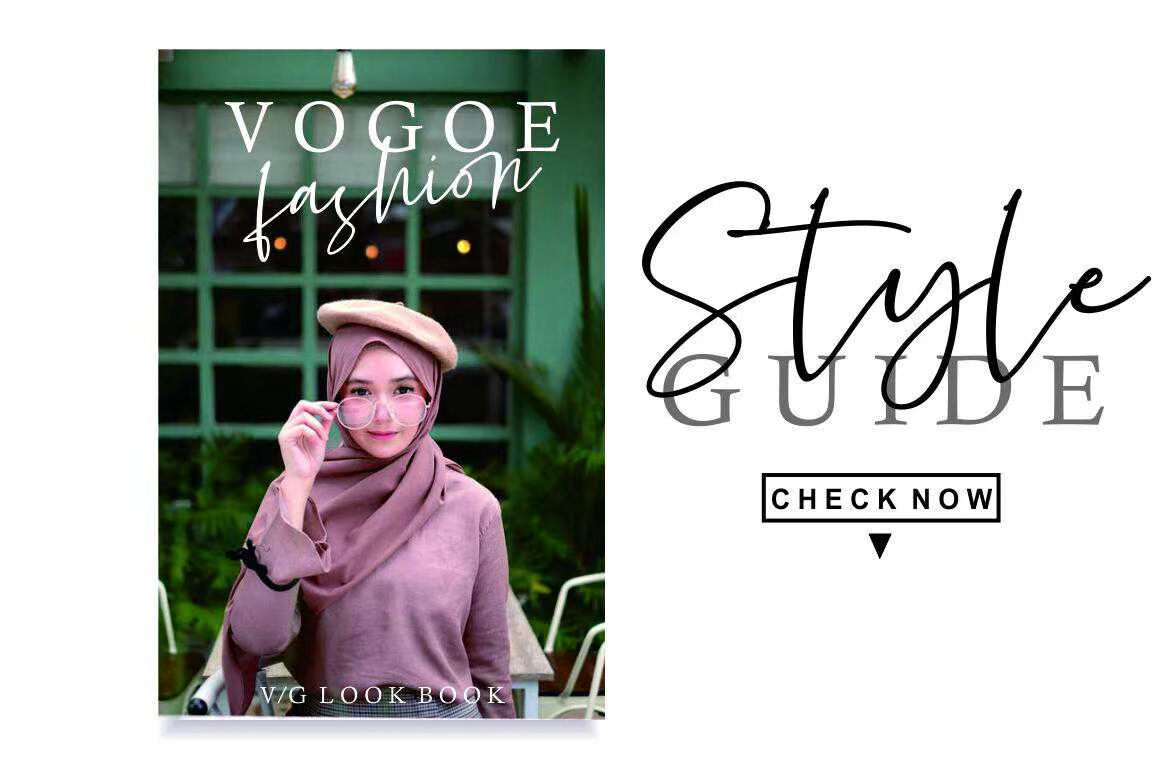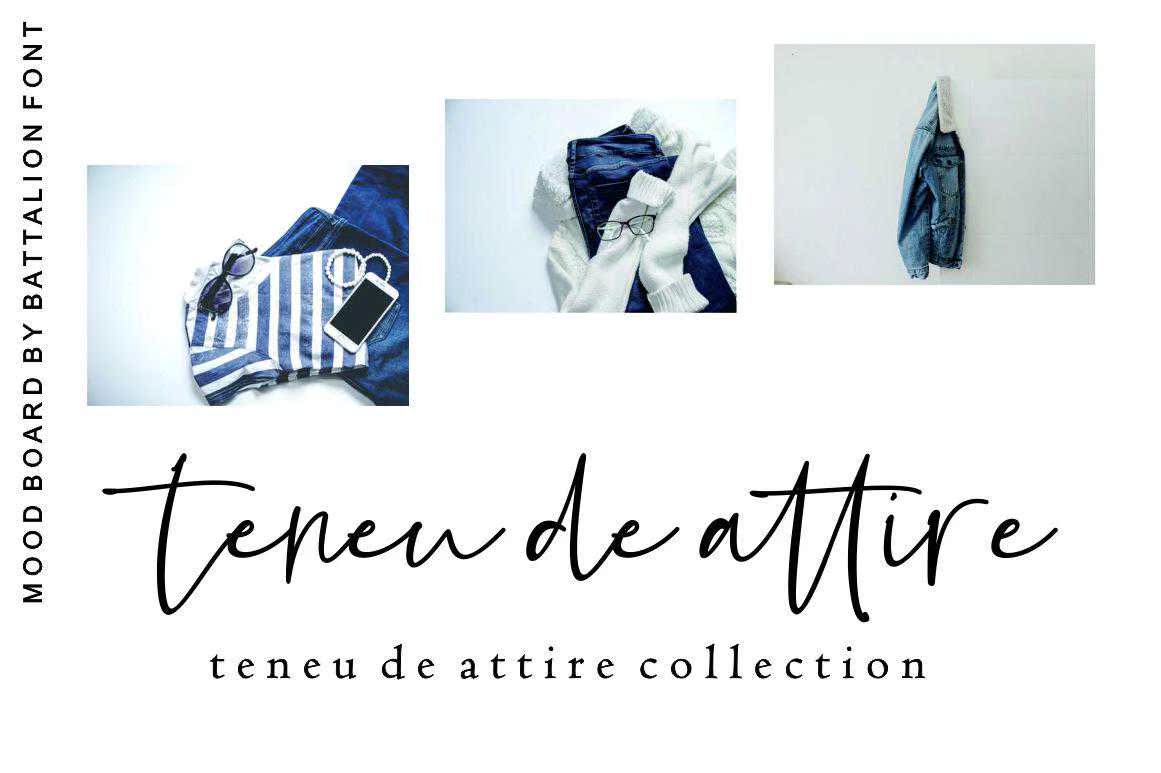
你好!!!介绍MaylestFont,Battalion。Battalion是一款非常适合您需要的字体和书写字体,具有很好的规范性和替代性。非常适合您的各种需要,例如:徽标、品牌、报价、杂志、包装产品、签名、横幅、贴子和其他。Battalion有多种语言和替代性以及多语言支持,如法语、,西班牙语、德语和其他语言。你下载它的目的是什么?你会得到:–OTFFILEhola!!!介绍MaylestFont,Battalion。Battalion是一款非常适合您需要的字体和书写字体,具有很好的规范性和替代性。非常适合您的各种需要,例如:徽标、品牌、报价、杂志、包装产品、签名、横幅、贴子和其他。Battalion有多种语言和替代性以及多语言支持,如法语、,西班牙语、德语和其他语言。你下载它的目的是什么?你会得到:–Otfile